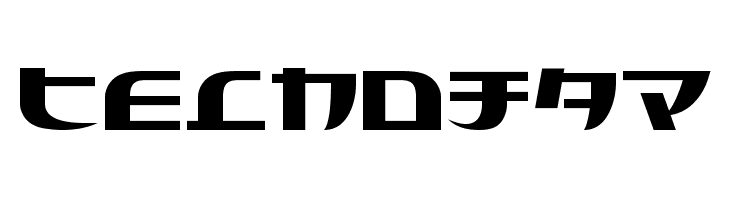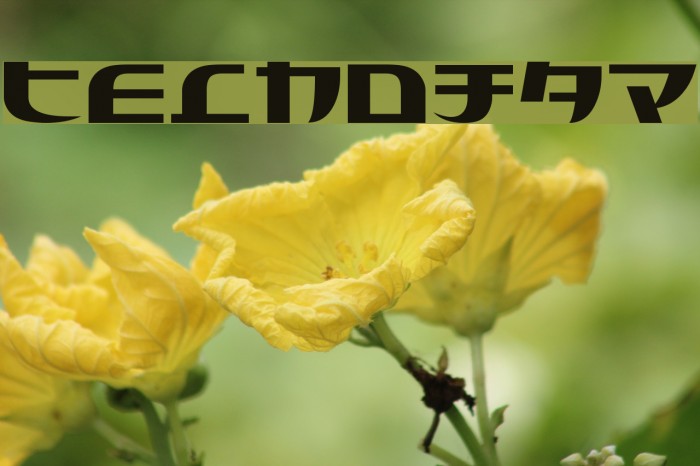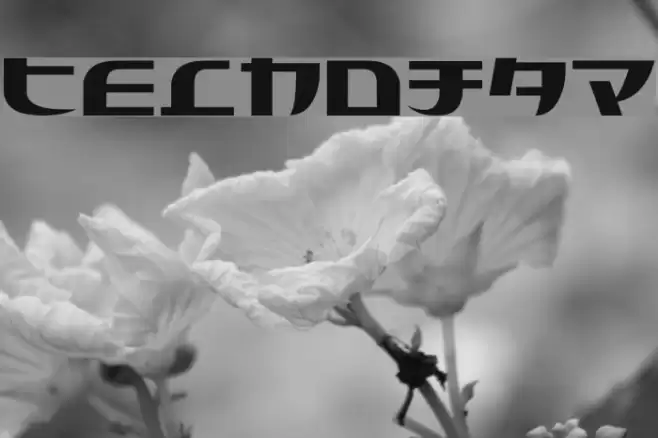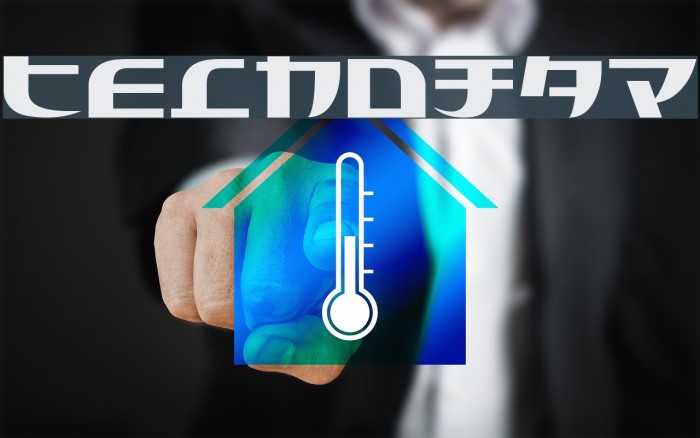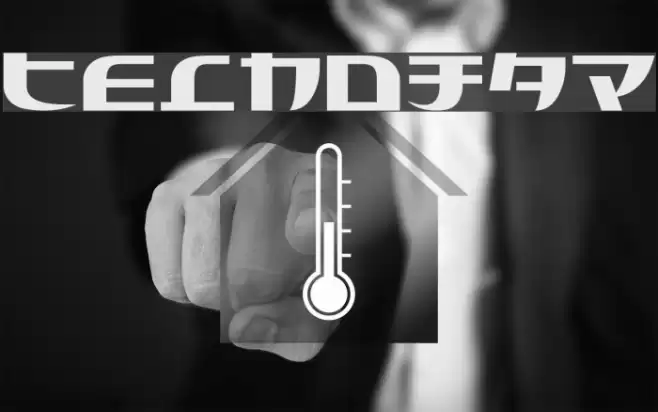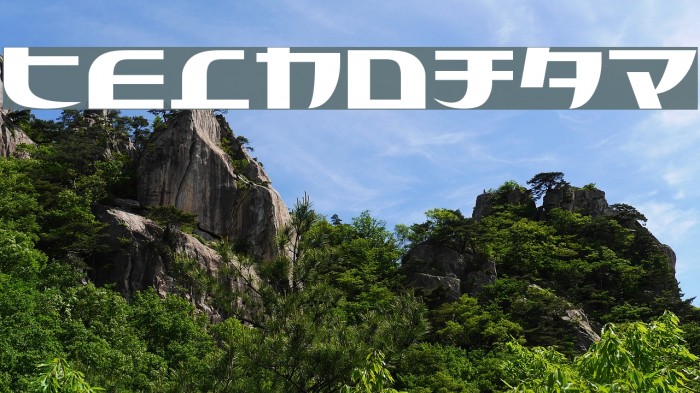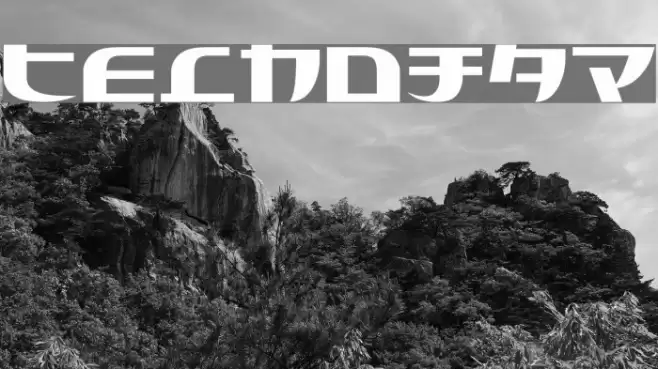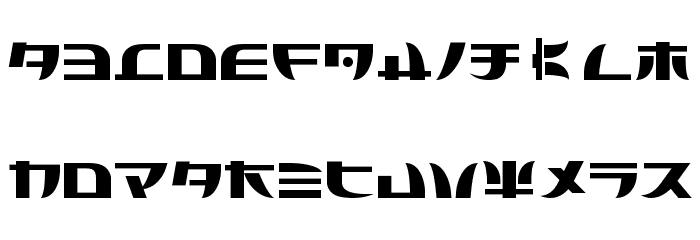
Tecnojap Font
| Anwendungsfall | Logos, Headlines |
| Vorgeschlagene Projekte | Ideal for technology branding, sci-fi movie posters, video game titles, and digital media. |